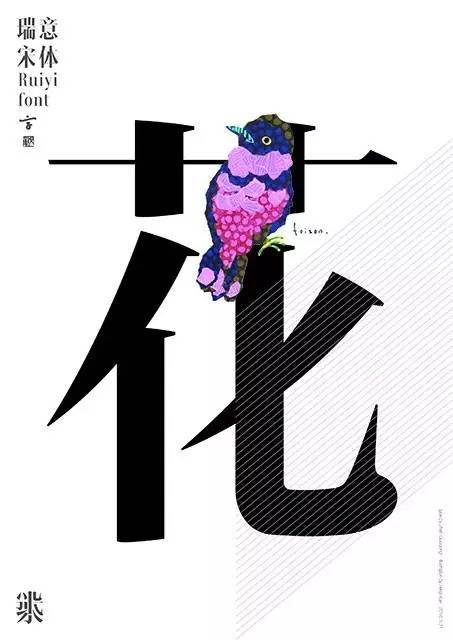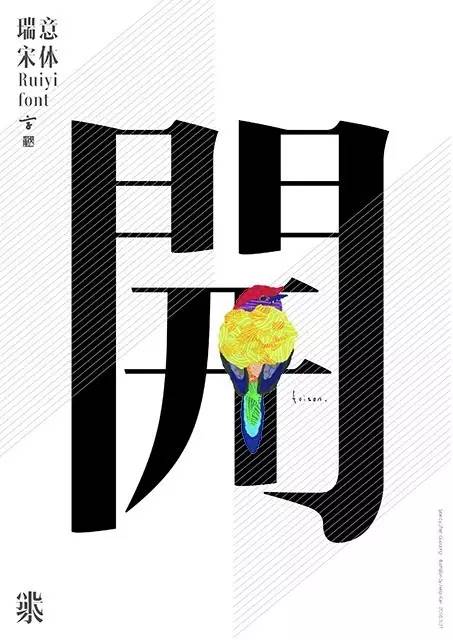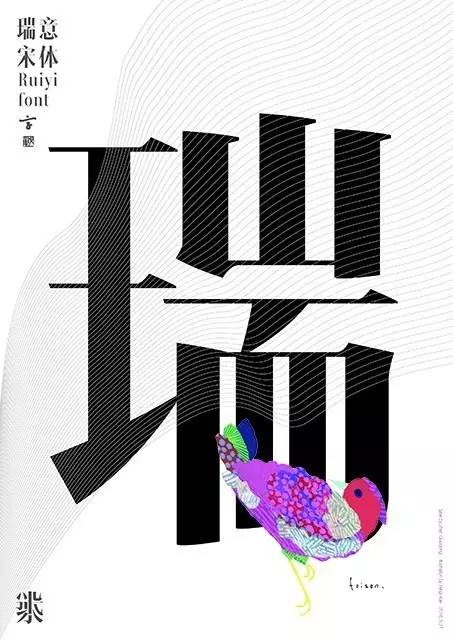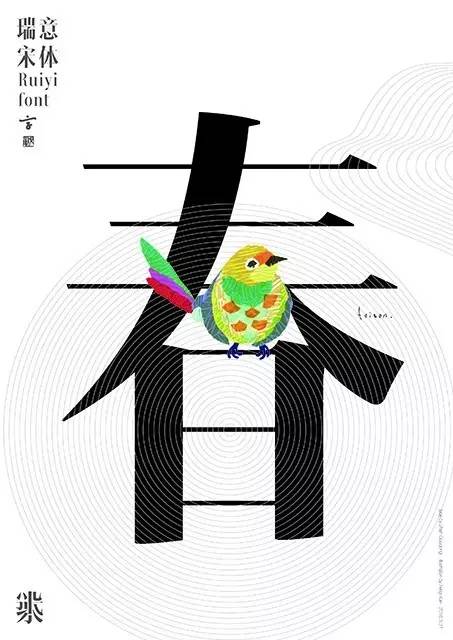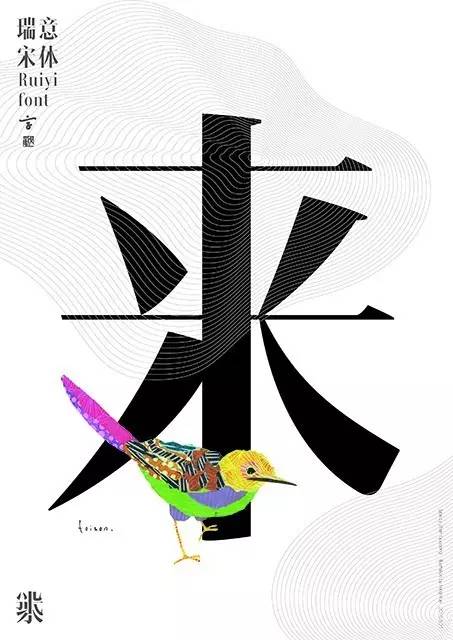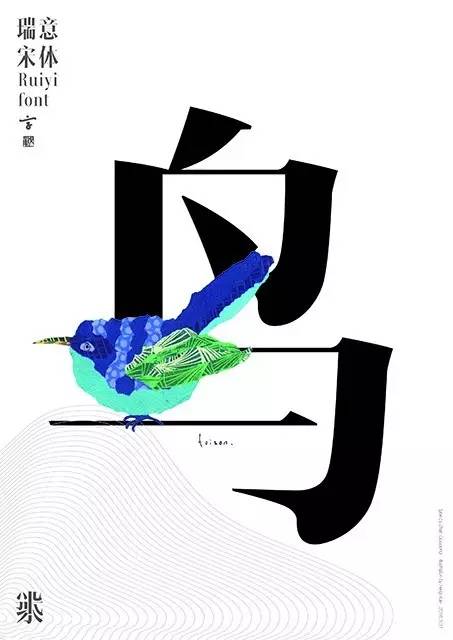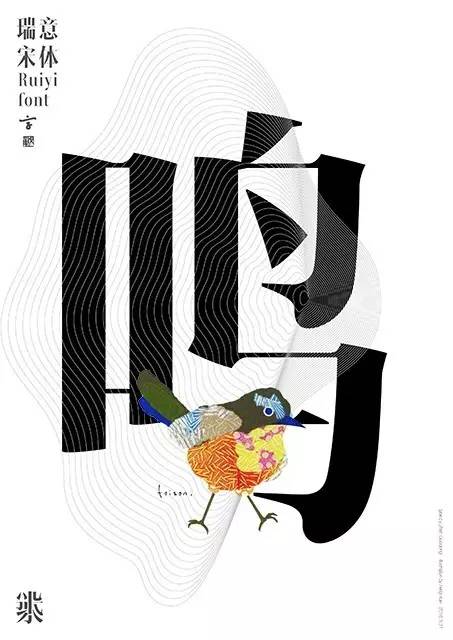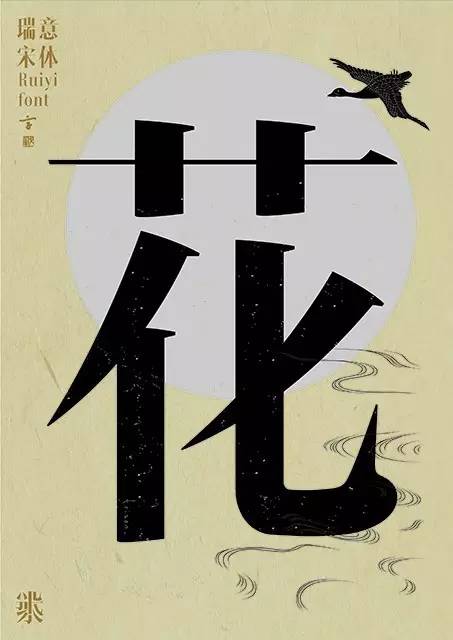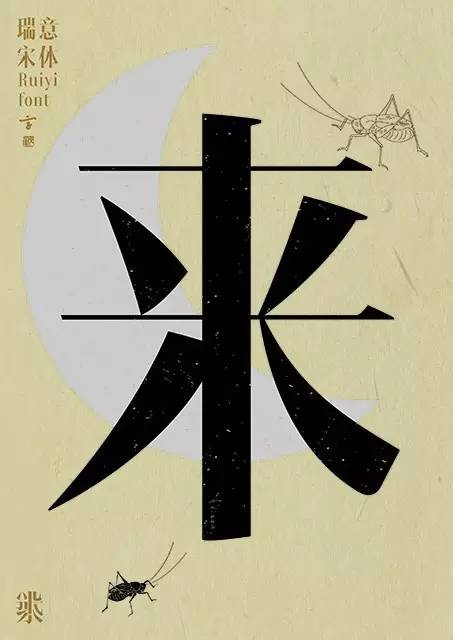
汉仪瑞意宋字体介绍,汉仪瑞意宋设计理念、案例
不同年代的字体,都有着其所处年代的时代特征,表达着当时的大众审美。
摩天大楼一般的高耸感、硬朗直线带来的速度感、线面强对比带来的凌厉感、微妙而有张力的曲线带来的力量感与精致感,同时又尽可能保留汉字书写的人文情怀,处处都表达着这个时代的审美取向。 ——主创设计师 战国栋
瑞意宋体有着摩天大楼般的高耸感、硬朗直线的速度感、线面强对比带来的凌厉感、微妙而有张力的曲线带来的力量感与精致感。
汉仪瑞意宋是2010年战国栋老师在日本留学时的毕业创作上开始的,围绕着“都市”“速度”“时尚”“高雅”等关键词展开创作,字样在日本发表后获得爱知县立艺术大学2011年度优秀毕业设计,被校图书资料馆收藏。回国后,瑞意宋体字样经过几番修改完善,于2012年4月正式签约汉仪字库。
瑞意宋手稿
设计理念
瑞意宋体为满足标题文字的版面存在感而设计
相对于大段的文章正文和小字号的说明文字,标题在版面中往往以精炼的词组、短句句式携带着文章的核心信息独立于文章正文之外,占据最重要的版面位置,最大的字号、鲜明的字体个性、宽阔的存在空间,在版面中以第一存在感的姿态进入阅读者的视线,迅捷有效的专递信息。
瑞意宋体为满足标题文字的版面存在感而设计。
2010
最初试做字样,寻找现代工业的造型感觉
2011
在日发表字样
2012
签约汉仪字库,加粗竖线笔画,去掉横竖,笔画搭接处的细节,增加横竖撇结合处的白空间,调整勾的形态
2014
最终字样,再次加粗竖画,为家族展开准备,再次调整竖勾造型
瑞意宋体的假想字身为W900、H1000,字面基准框W770、H960的窄幅字面设定,使得瑞意宋体在固定的行空间内、在同等字数的情况下拥有宽广的字间距,让标题文字的存在空间更为从容优雅。
瑞意宋体中宫适当放松,文字内外空间均匀布局,重心上扬,结合狭长的字面,在整体字形上给人舞者般束身收腰、亭亭而立的印象。
笔画设计
横画和竖画的粗细比例达到1:11,这种从玻璃幕墙建筑中抽离出来的强列的线面对比配合勾提的犀利形态,给人带来极致的感官刺激。宋体横端的三角形元素,更是打破了传统的固有状态,设计得扁平尖锐似箭头的形状强化了快节奏生活的速度感。
同时,在笔画的曲线上,放弃了现代字体中常用的几何圆切曲线,更多的使用了富有弹性的有机曲线,为文字注入人文情怀,使之更有温度感,满足人们的精神需求。
瑞意宋体作为大标题用字体,在放大字号时除了在笔画造型上可以看到精致的细节,具有造型上的可视美感外,在笔画搭建上同样注意了白空间的变化,如“木”“表”等字,笔画的结合处做了半融合的处理,避免了粗重笔画交和成大面积的黑色,同时丰富了文字负空间的细节。
以横画为主的字,适当加粗横线并等比例放大顿角,以增强文字的存在感;以竖画为主的文字中,为保证整体灰度,适当减小竖画粗度。
结构设计
瑞意宋体的字面以880:1000的狭长字面呈现,同时重心抬高,增大字间距,以使瑞意宋体具有高耸、独立、高雅的气质。
设计难点
首先就是狭长的字面与粗重的竖线笔画之间的矛盾,要在狭小的字面空间内安排多笔画字形,在横画的弱化情况下要保证字形的完整性,同时又要保证字库整体的均匀灰度,如何使这些看似矛盾的要素达到一个相对平衡的状态,是非常困难的一件事情。
其次,这是一款强调感受又不能过分夸张感受的标题字体,又在曲线上使用了弹性的有机曲线,在字库的多人协同生产的状态下,没有了以往的几何制图标准,设计师们要透彻地理解这款字体的气质,一切以整体感受为依据工作的时候,设计师们之间对感觉把控的一致性就显得极为重要,这也是这款瑞意宋体在设计制作和生产上最为困难的地方之一。
西文设计
为了适应现今多种语言排版环境的需要,解决拉丁文字搭配选择的困难,我们在做汉字字符的同时,也为瑞意总体量身设计了与之匹配的拉丁文字、希腊文字、西里尔文字、日文假名、注音符号等千余字符。
为了在中英文混排的情况下,使得行线整齐平稳,我们在拉丁字母的设定上,加大了X的高度,相对应缩小了上升部和下沉部的高度,同时与汉字的基线配合降低了拉丁基线。在字宽上瑞意拉丁借鉴了古罗马体的比例,字符间距也相应拉大,以此使得瑞意拉丁具有现代又不失传统的高贵气质。
应用范围推荐
具有内在个性美而不张扬的大标题,汉仪瑞意宋比较适合以大字号大间距的方式使用,在原始字距的情况下,20pt以上字号使用为佳。
字体气质
现代 / 工业感 / 坚硬 / 个性张扬 / 时尚 / 有力 / 独立 / 高雅
应用环境
房地产 / 服饰 / 美妆 / 汽车/ 奢侈品等